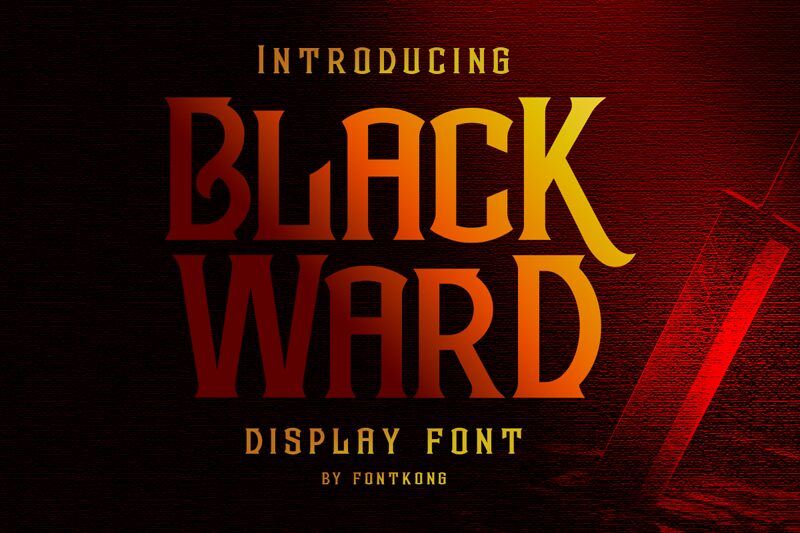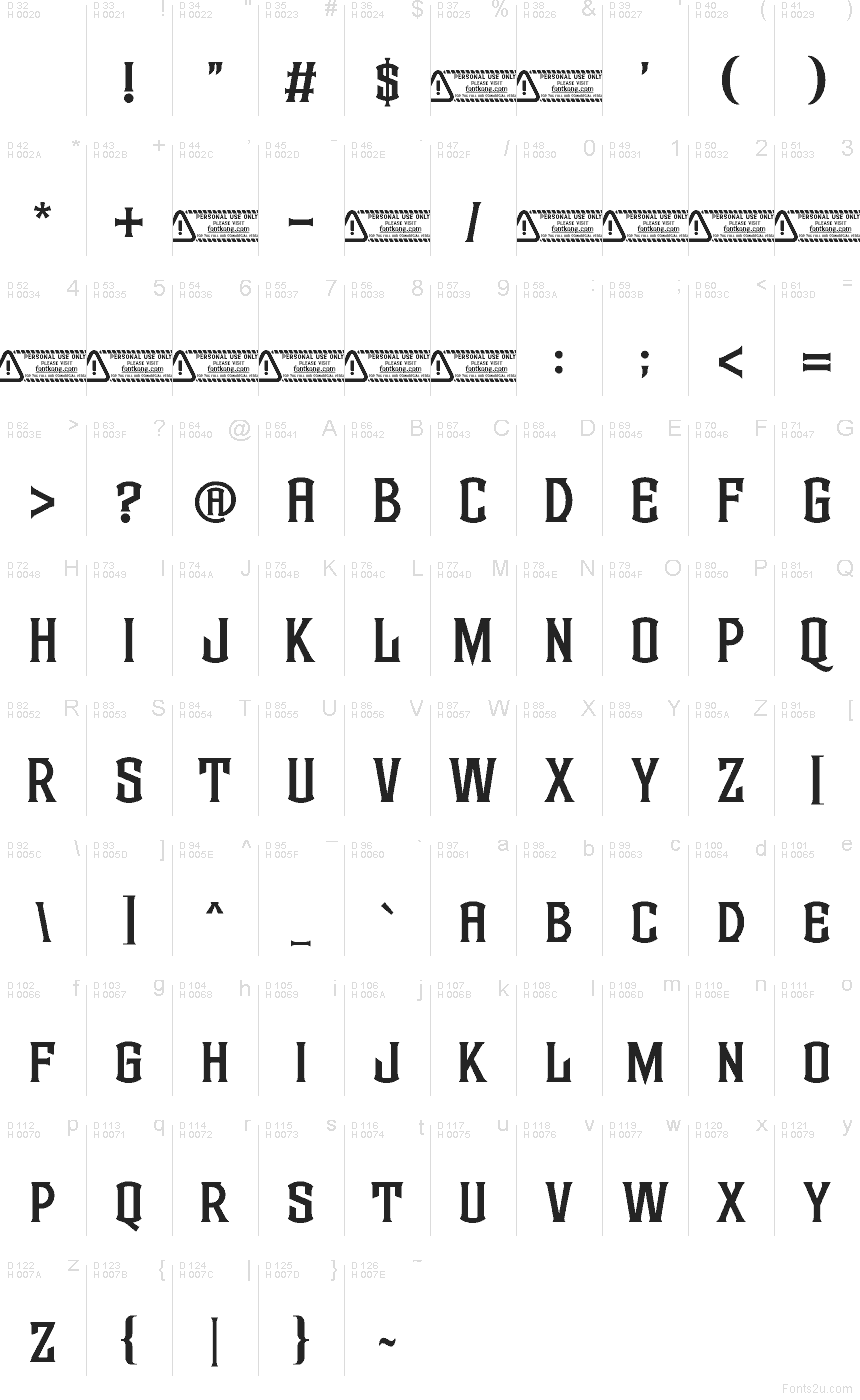
Blackward, da Kong Font, é uma fonte gótica gratuita em caixa alta, com formas altas e divididas, além de pontas afiadas que conferem às letras um toque entalhado de estilo clássico. As maiúsculas misturam a atmosfera do blackletter com um ritmo mais limpo de pôster, fazendo com que a fonte pareça cerimonial e severa, sem se tornar confusa.
É perfeita para branding de moda dark, flyers de música, capas de fantasia, rótulos de bares e merchandising inspirado em tatuagens, onde poucas palavras precisam daquela pulsação medieval austera. Como fonte gratuita, a Blackward também funciona muito bem para cartões de título, monogramas e títulos curtos, já que o estresse vertical estreito e as junções em forma de lâmina mantêm os caracteres dramáticos mesmo em espaços apertados.